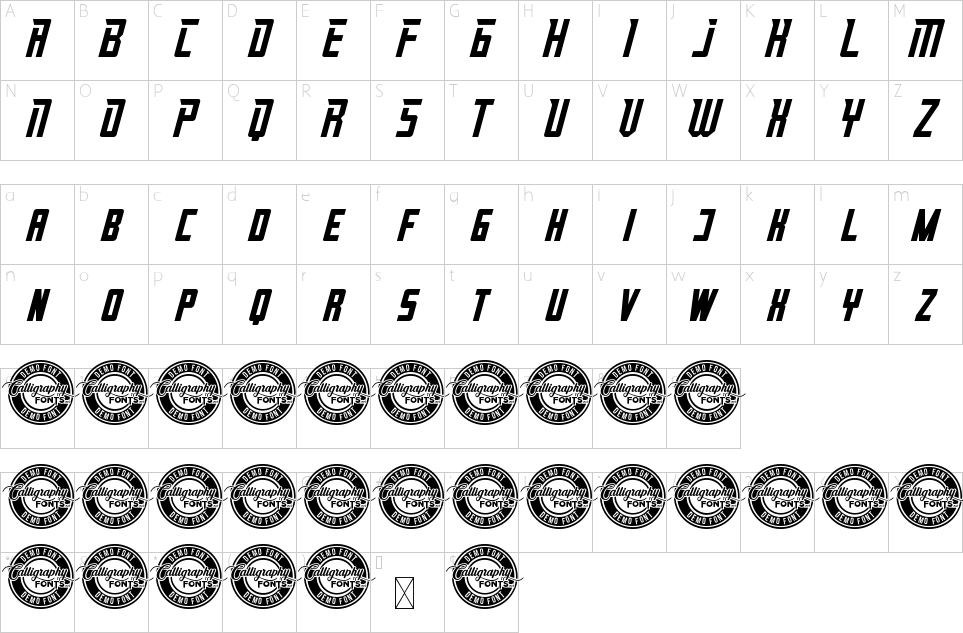
Patriotics Font é uma elegante e vibrante escolha para aqueles que valorizam a cultura e história do Brasil, oferecendo nuances únicas capazes de dar vida a suas mensagens com força e estilo. Este design foi cuidadosamente criado por calligraphyfonts, e embora as especificações técnicas não sejam nossas, sua grande popularidade indica que ela está entre os fontes mais amadas para uso em projetos gráficos. Com seu design detalhado inspirado na tradição do Brasil, Patriotics Font tem o potencial de tornar um projeto de identidade visual ainda mais expressivo e vibrante. Seja em sua aplicação em uma etiqueta, logotipo ou até mesmo no título de um evento importante, essa fonte traz ao seu design uma sensação que combina a elegância do nosso país com a força da arte tipográfica. Estamos orgulhosos de oferecer essa fonte gratuita para download tanto para Windows quanto Mac, proporcionando aos nossos usuários brasileiros a oportunidade de personalizar seus trabalhos gráficos com um estilo único e vibrante.